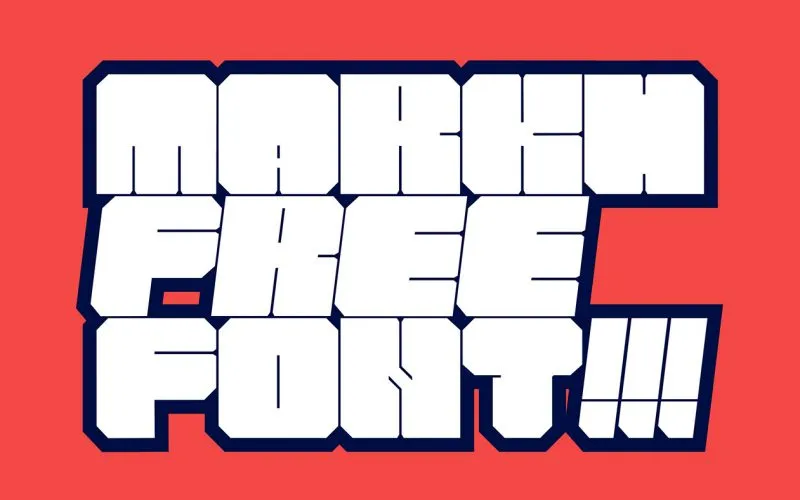
Introduzimos Markh Typeface. Desenhada por Tikhon Reztcov, esta é uma fonte sans-serif bold e limpa com 2 tipos de fontes e suporte multilíngue. Markh foi projetado para trabalhar bem tanto em grandes quanto em pequenos tamanhos. Ele é perfeito para projetos de marca, design de mobília, embalagens de produtos, cabeçalhos de revistas – ou simplesmente como um texto estiloso sob qualquer imagem de fundo. Suave e elegante, Markh oferece uma solução versátil que certamente enriquecerá seu projeto visual.